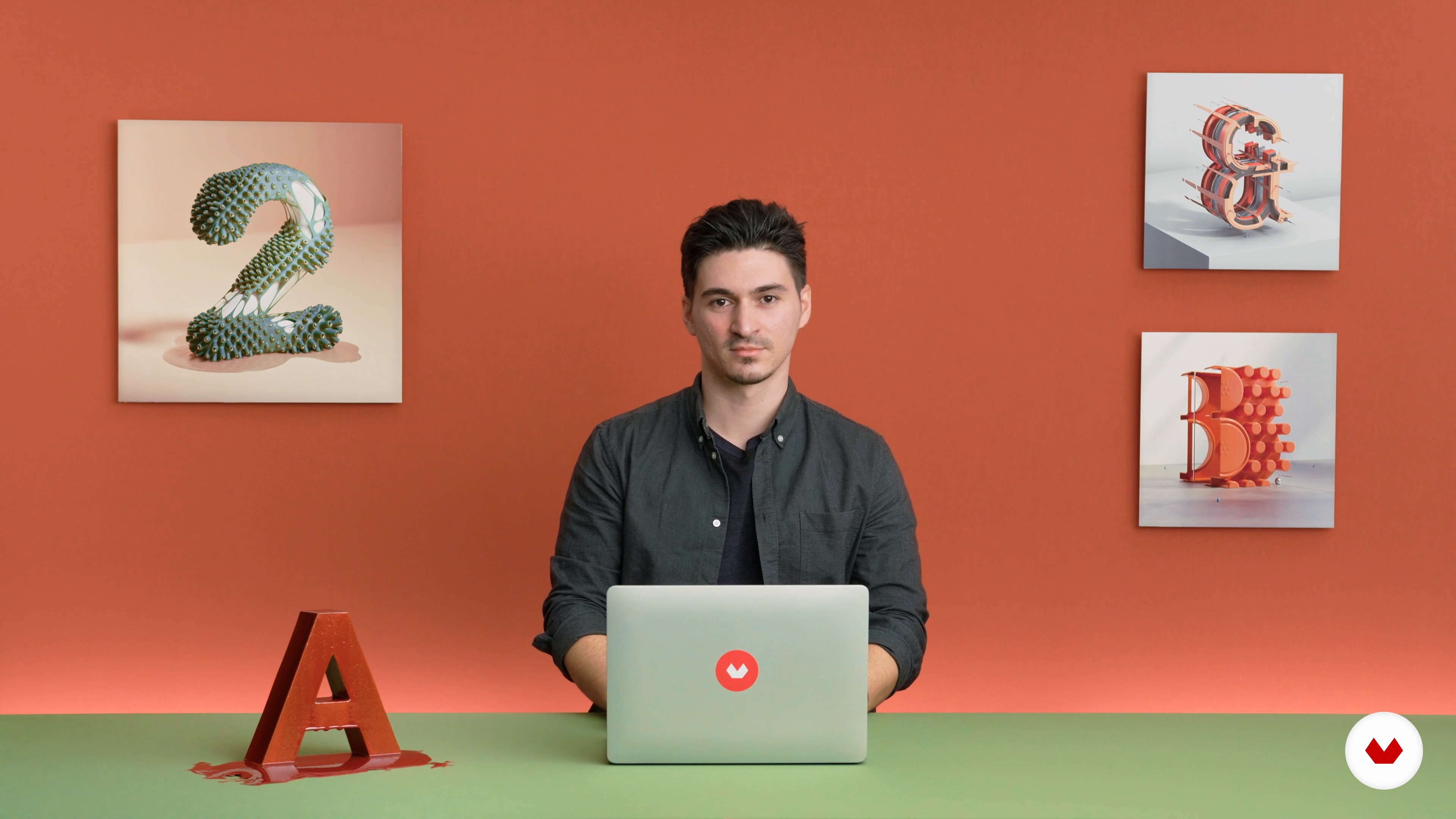
Typographie 3D : créez des lettres uniques sur Blender
Un cours proposé par Alper Dostal , Graphiste et artiste 3D
“Vous découvrirez tout d'abord qui je suis, ce que je fais et comment j'ai suivi ma passion.”
Dans cette leçon, Alper Dostal aborde le sujet : Présentation, qui fait partie du cours Domestika en ligne : Typographie 3D : créez des lettres uniques sur Blender. Découvrez différentes techniques pour modéliser des lettres en 3D sur Blender et jouez avec des contrastes surréalistes de couleurs, matières et textures.
“Sur moi Salut, bienvenue au cours. Je suis Alper Dostal, designer et artiste 3D. Je suis né et j'ai grandi à Vienne et mes parents viennent de Turquie. Mes intérêts créatifs ont été fortement influencés par mes parents, principalement à cause de mon père qui travaille dans le domaine de la vidéo et de la photographie. Enfant, j'avais le droit de jouer de temps en temps avec ses caméras, essayez-le et faites des vidéos vous-même. Plus tard, nous avons eu un ordinateur sur lequel j'ai commencé à dessiner, construire des sites web et me tamponner dans un logiciel 3D. A l'école, j'étais bon en ...”
Alper Dostal est un graphiste et artiste 3D originaire de Vienne, en Autriche. En 2011, il obtient son diplôme de graphisme et de communication et commence à travailler dans ce domaine. Avec le temps, il s’intéresse de plus en plus à la 3D et finit par se consacrer exclusivement au graphisme. Il a réalisé des visuels et des typographies en 3D pour des clients comme Teka, General Electric ou encore Samsung.
La modélisation 3D est son outil privilégié pour visualiser des phénomènes déjouant les lois de la physique comme du bois fondu ou du béton caoutchouteux. Il tire notamment son inspiration du design minimaliste de Dieter Rams et des œuvres surréalistes de Salvador Dalí. Ses œuvres d’art fondues issues de la collection « Hot Art Exhibition » ont été présentées à Bergame et au salon Art Basel de Miami. Elles sont également apparues dans plusieurs revues d’art et de design.